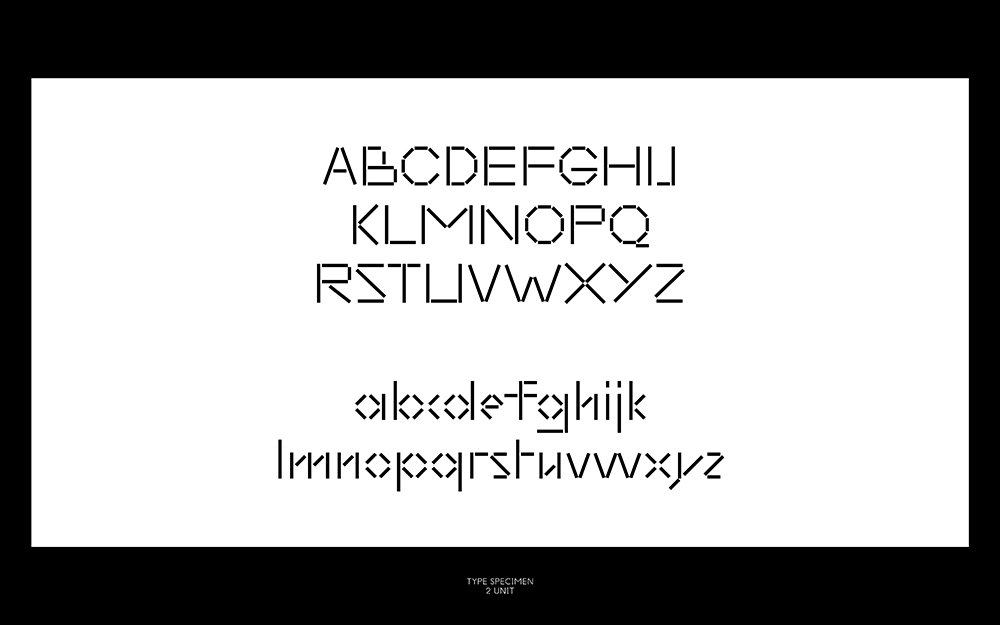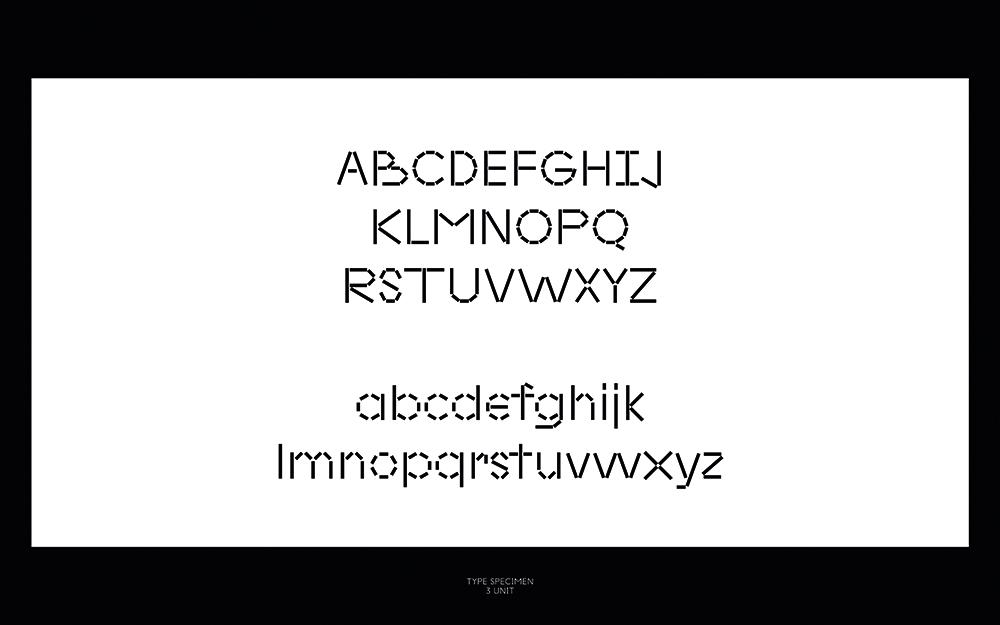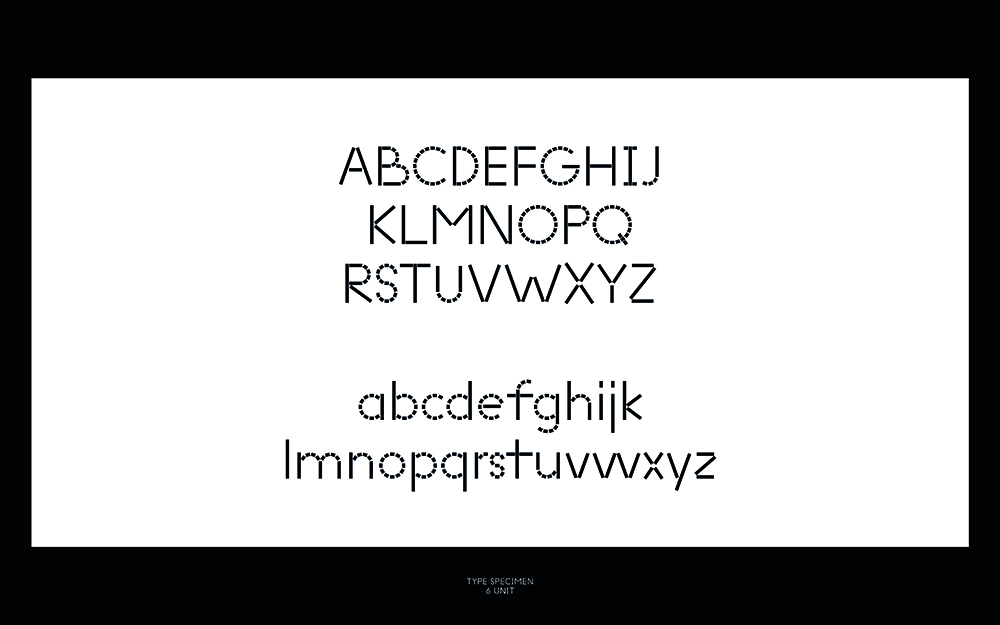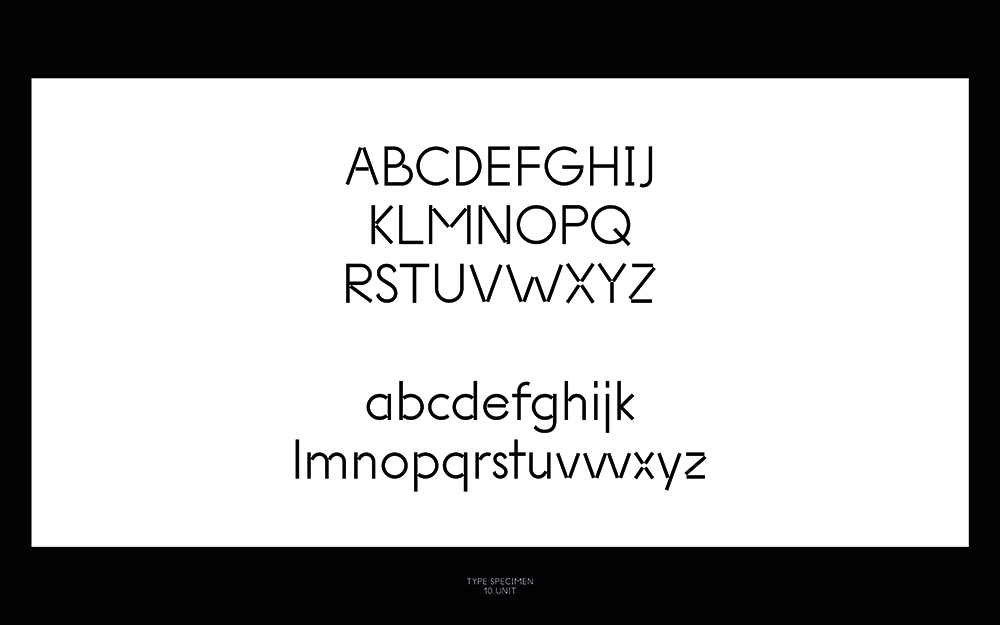
시카고 현대미술관의 새로운 비주얼 아이덴티티
시카고 현대미술관의 아이덴티티 작업에는 새로운 서체 세트가 포함되었는데 이 서체는 프랑스 출신의 디자이너 칼 나브로가 미술관을 위해 직접 고안한 것이다. 나브로는 미술관의 가치와 다양한 프로그램을 떠올릴 수 있도록 그리드 컨셉을 고려한 사각형의 결합을 통해 재치 넘치는 느낌부터 고전적인 느낌까지 다양한 시리즈의 서체를 제작했다.
시카고 현대미술관의 새로운 비주얼 아이덴티티
시카고 현대미술관의 아이덴티티 작업에는 새로운 서체 세트가 포함되었는데 이 서체는 프랑스 출신의 디자이너 칼 나브로가 미술관을 위해 직접 고안한 것이다. 어떤 형태의 서체를 만들지 정확한 아이디어를 떠올리지 못했기 때문에 서체 개발은 꽤 어려운 도전 과제였다. 메비스 앤 판 되르센은 서체 디자이너 몇 명과 대화를 나눴고 다양한 시작점을 기준 삼아 테스트를 진행했다.
최종적으로 그들은 프랑스의 그래픽 디자이너인 칼 나브로와 함께 4개의 사각형을 하나의 단위로 만든 서체 작업을 진행하기로 했다. 이 서체는 다양한 상황에 맞춰 크기를 키우거나 변형할 수 있게 디자인되었다. 나브로는 미술관의 가치와 다양한 프로그램을 떠올릴 수 있도록 그리드 컨셉을 고려한 사각형의 결합을 통해 재치 넘치는 느낌부터 고전적인 느낌까지 다양한 시리즈의 서체를 제작했다.
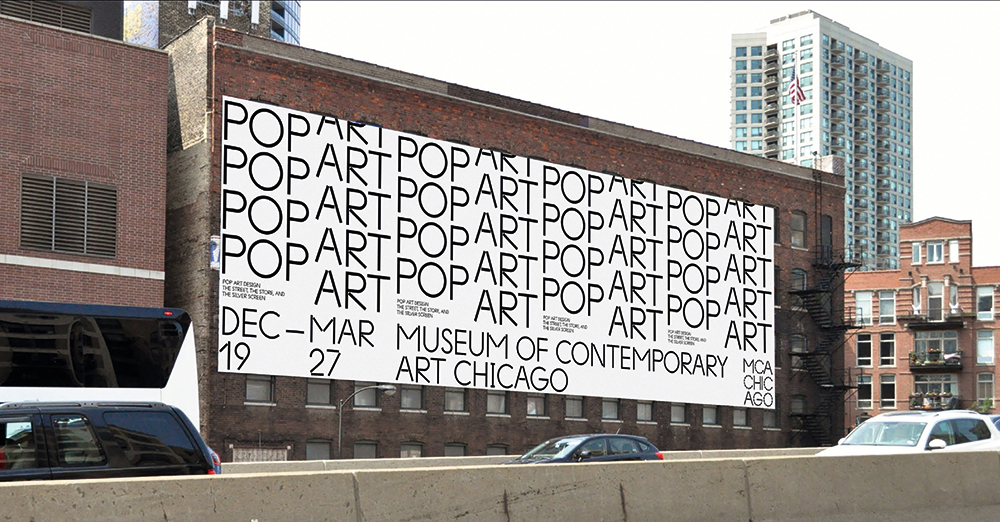
폰트는 두 기간으로 나뉘어 디자인되었다. 첫 단계는 2014년 여름 내내 진행되었는데 그 시간 동안 메비스 앤 판 되르센과 나브로는 단위 시스템이 제작되는 과정을 따라가며 폰트가 변화하는 방식을 정의했다. 최종 폰트는 2014년 12월에서 2015년 3월 사이에 디자인되었다. 각각의 스타일은 전체적으로 단위의 숫자에 따라 1-2주 정도가 걸렸다. 나브로는 메비스 앤 판 되르센과 긴밀하게 협업했고, 폰트를 개발하는 동안 여러 번의 논의를 거쳤다.
폰트의 커스터마이징이 시작되고 사이니지와 아이코노그래피에 폰트를 실제로 적용하기 시작한 이후에 나브로는 MCA 디자인 팀과 더 많은 대화를 나누게 되었다. MCA 디자인 팀은 폰트를 다소 수정할 필요가 있다고 언급했다. 예컨대 중간 굵기를 더 추가해야 한다거나 이탤릭체를 만들고 몇몇 글리프를 추가해 달라는 요청들이었다.
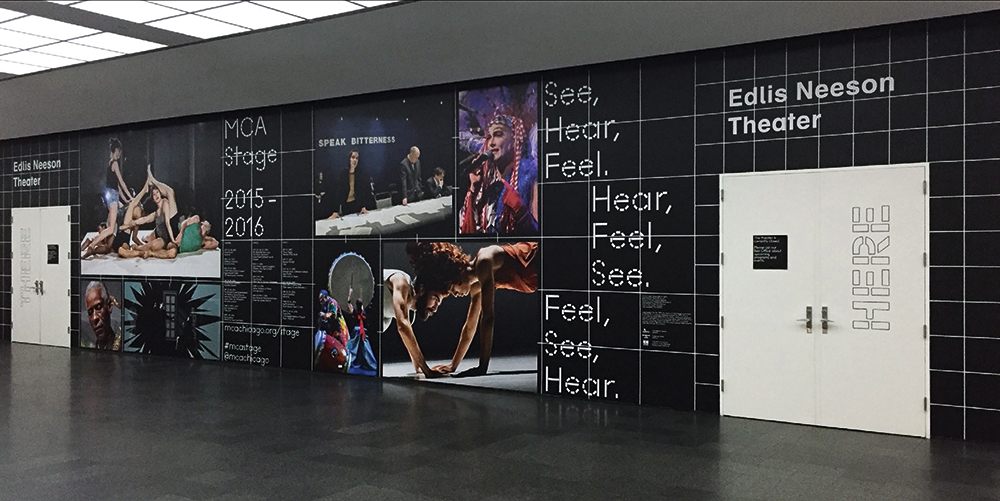
MCA의 새로운 아이덴티티는 단순하고 현대적인 스타일을 극단까지 추구한 것으로 MCA만의 독특한 개성을 반영하고 있다.
사람들은 나브로에게 왜 이 서체의 각진 형태들이 절대 서로 연결되지 않느냐고 묻곤 한다. 우선 나브로는 사람들이 물어보는 그러한 요소 덕분에 폰트에 개성이 생겼다고 주장한다. 하지만 더 중요한 것은 이런 형태가 건축의 이미지를 전달한다는 점이다. 각각의 글자 너머에서 건축의 뉘앙스와 감각, 즉 구조와 뼈대에 대한 아이디어를 엿볼 수 있게 디자인했다는 것이 핵심이다.
칼 나브로(월터 와튼), KARL NAWROT(AKA WALTER WARTON)
그래픽 디자이너
드로잉과 모형 제작, 서체 디자인, 일러스트레이션을 결합하여 아이 같은 느낌의 선과 과격한 형태, 건축 구조, 초현실적으로 왜곡된 공간 사이에 존재하는 잠재적인 내러티브를 탐구한다.
시카고 현대미술관(MUSEUM OF CONTEMPORARY ART CHICAGO)